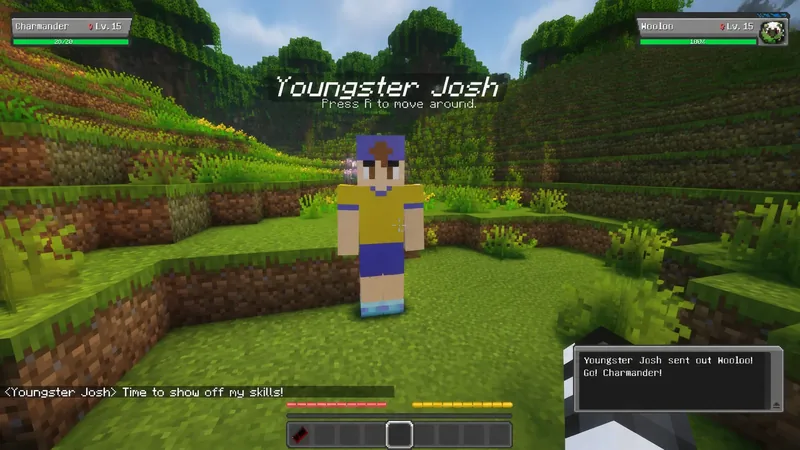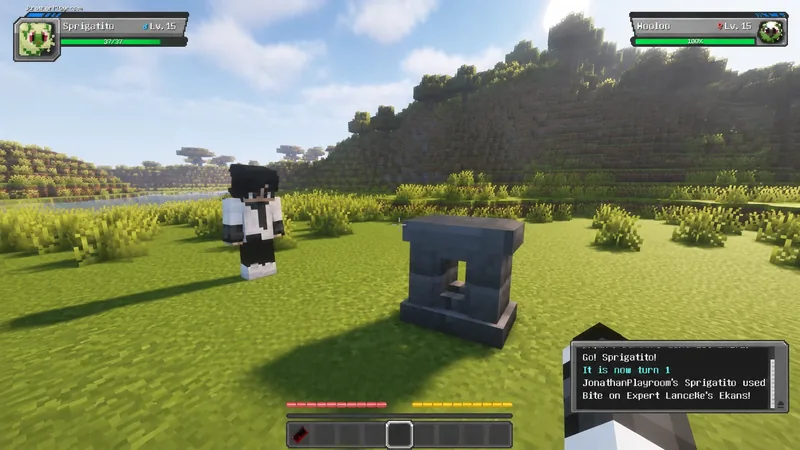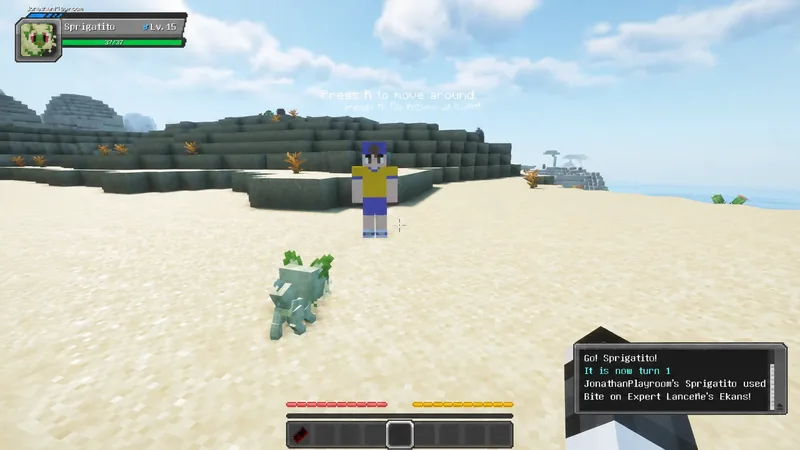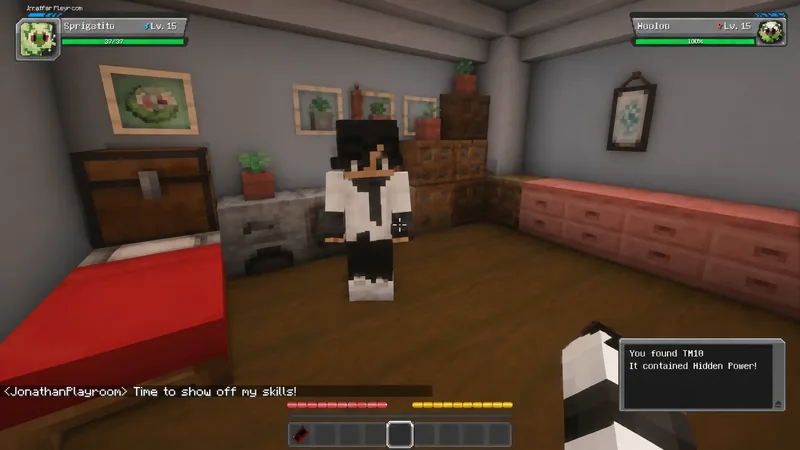
Minecraft Font
Кратко о проекте
Minecraft Font Addon — простой, но крутой ресурс-пак, который меняет стандартный тонкий шрифт Minecraft на более жирный и читаемый вариант, идеально подходящий для кириллицы и других языков. Если ты устал squint’ить на меню, чаты и таблички, этот мод добавит четкости и стиля твоему игровому интерфейсу.
Как выглядит в игре
С этим аддоном текст в игре становится более визуально выразительным — даже длинные сообщения или таблички с названием городов и построек читаются легко. Он работает для Bedrock Edition (PE и Windows 10), а отдельная версия есть и для Java.
Основные возможности Minecraft Font Addon:
• Замена стандартного тонкого шрифта на жирный
• Поддержка кириллицы и других нестандартных алфавитов
• Улучшенная читаемость текста в чате, интерфейсе и на табличках
В отличие от других визуальных модов и паков, которые добавляют анимации или декоративные эффекты, этот ресурс-пак сфокусирован исключительно на функциональности текста. Он не перегружает игру и не изменяет её механику, но делает интерфейс более современным и удобным для чтения.
Идеально подходит для игроков, которые часто общаются в чате, ведут сервера на русском языке или просто любят, когда интерфейс выглядит аккуратно и профессионально. Добавляет чистый визуальный апгрейд без сложных настроек и конфликтов с другими модами.
Если хочется сделать Minecraft более “читабельным” и стильным, особенно для мультиплеера и серверов с русским текстом — Minecraft Font Addon станет простым, но заметным улучшением.